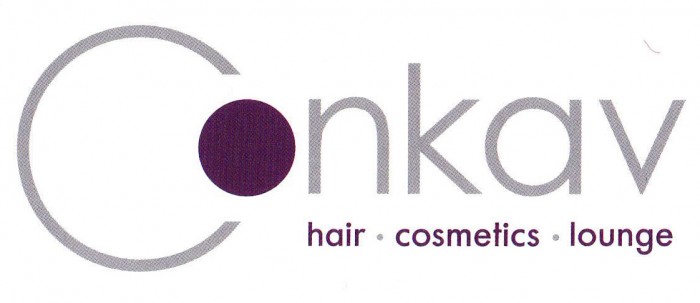
Avantgarde-ähnliche Schrift mit spitz zulaufendem V
zuerst dachte ich es wäre die Avantgarde, aber das V läuft unten spitz zusammen
und das K ist auch ein wenig anders. Zur Identifizierung kann vllt. auch die
Aufzählungen "hair cosmetics lounge" helfen.
Ich probier die Futura mal aus.
Ich musste ein paar KleinIgkeiten modifizieren, aber jetzt passt es.
Da wurde sicherlich ein Futura-Klon verwendet. Für die Headline
habe ich nun die Futura Lt BT und für die Subline die Futura Md BT